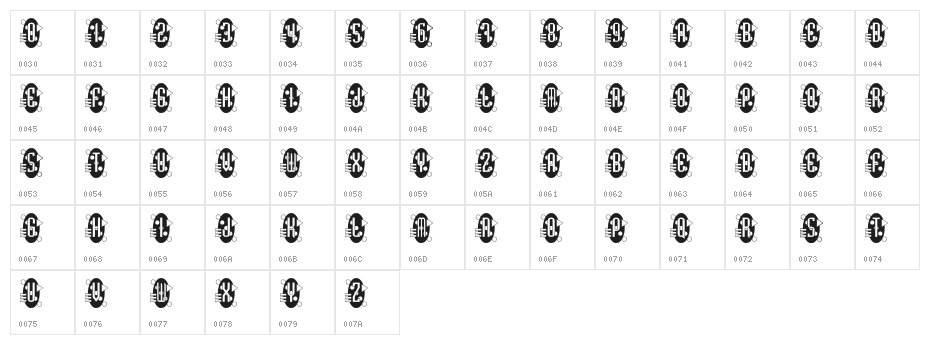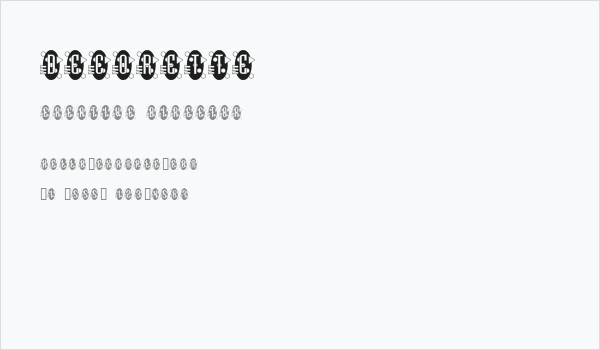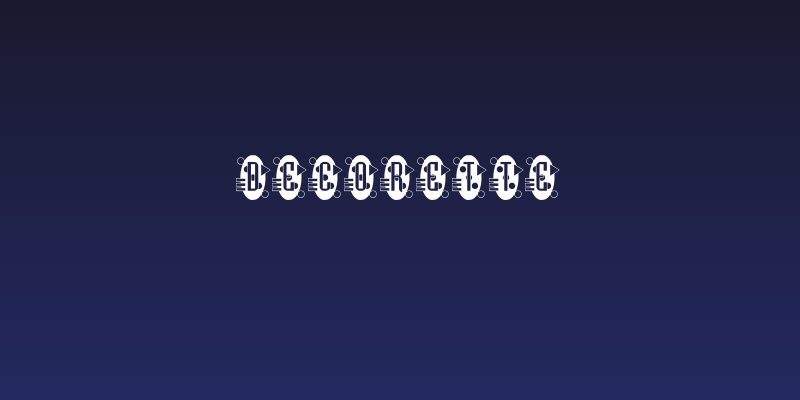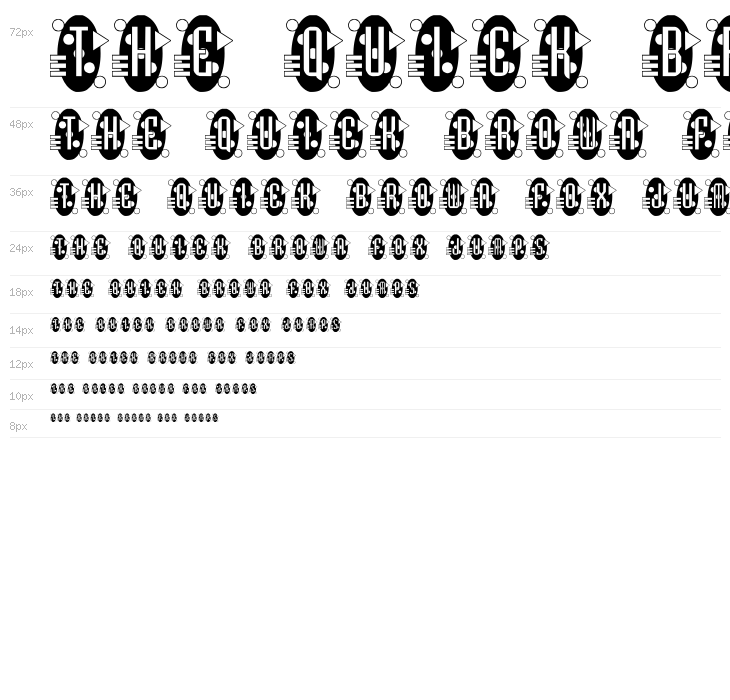
Decorette Font
| Gesamtstil | Retro-Futuristic |
| Anwendungsfall | Logos, Posters, Headlines |
| Vorgeschlagene Projekte | Ideal for sci-fi themed projects, retro posters, video game graphics, and unique branding materials. |